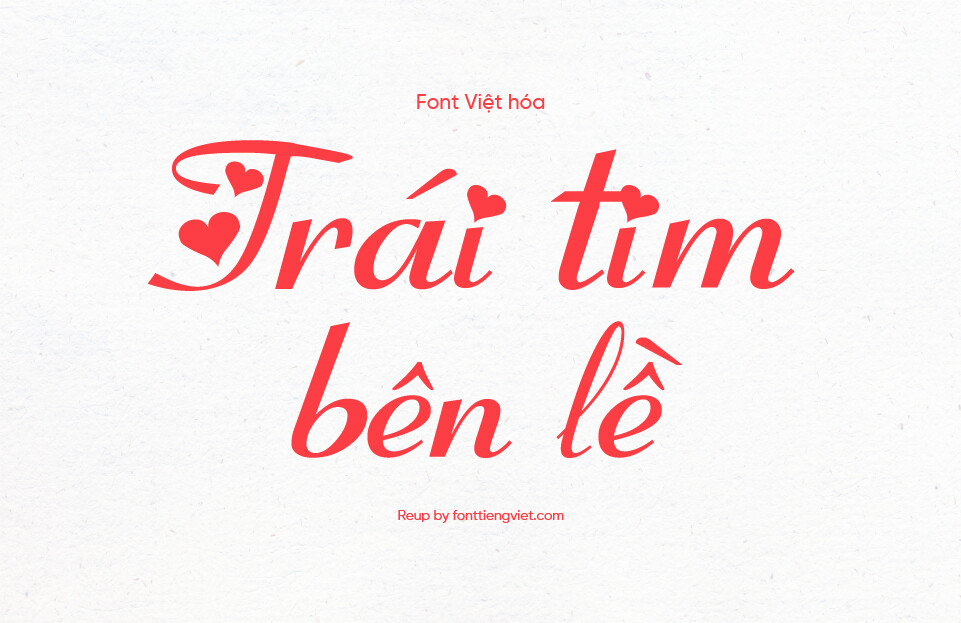
Font việt hóa Fiolex girl – Font cho Valentine
Font việt hóa Fiolex girl – Font cho Valentine – Lựa chọn hoàn hảo cho mùa yêu thương
Trong thế giới thiết kế đồ họa, việc lựa chọn một Font Miễn Phí phù hợp đóng vai trò quan trọng trong việc truyền tải thông điệp. Đặc biệt vào dịp lễ tình nhân, Font việt hóa Fiolex girl – Font cho Valentine nổi lên như một công cụ đắc lực giúp các bạn học sinh và thầy cô tạo ra những sản phẩm sáng tạo đầy cảm xúc. Đây là bộ phông chữ mang phong cách bay bổng, nữ tính với những chi tiết trang trí hình trái tim nhỏ nhắn được lồng ghép tinh tế vào từng nét chữ, tạo nên sức hút khó cưỡng cho mọi tấm thiệp hay món quà tinh thần.
Sức hấp dẫn của Font việt hóa Fiolex girl – Font cho Valentine
Lý do khiến Font việt hóa Fiolex girl – Font cho Valentine trở nên phổ biến chính là sự kết hợp hài hòa giữa nét vẽ thanh mảnh và biểu tượng tình yêu. Trong môi trường học đường, các em học sinh có thể sử dụng phông chữ này để thiết kế báo tường, trang trí nhãn vở hoặc làm video ngắn tặng bạn bè. Nhờ bản việt hóa chuẩn, người dùng không còn lo lắng về lỗi gõ dấu tiếng Việt, giúp quá trình sáng tạo trở nên mượt mà và chuyên nghiệp hơn bao giờ hết.
Ứng dụng thực tế trong giáo dục và thiết kế
Bên cạnh việc trang trí, bộ chữ này còn rất hữu ích cho các hoạt động ngoại khóa tại nhà trường. Thầy cô có thể dùng nó để thiết kế slide bài giảng về chủ đề gia đình, bạn bè nhằm thu hút sự chú ý của học sinh. Sự mềm mại của các ký tự giúp giảm bớt vẻ khô khan của văn bản thuần túy, thay vào đó là một diện mạo mới mẻ, gần gũi và đầy tính nghệ thuật.
Kết luận về bộ phông chữ tình yêu